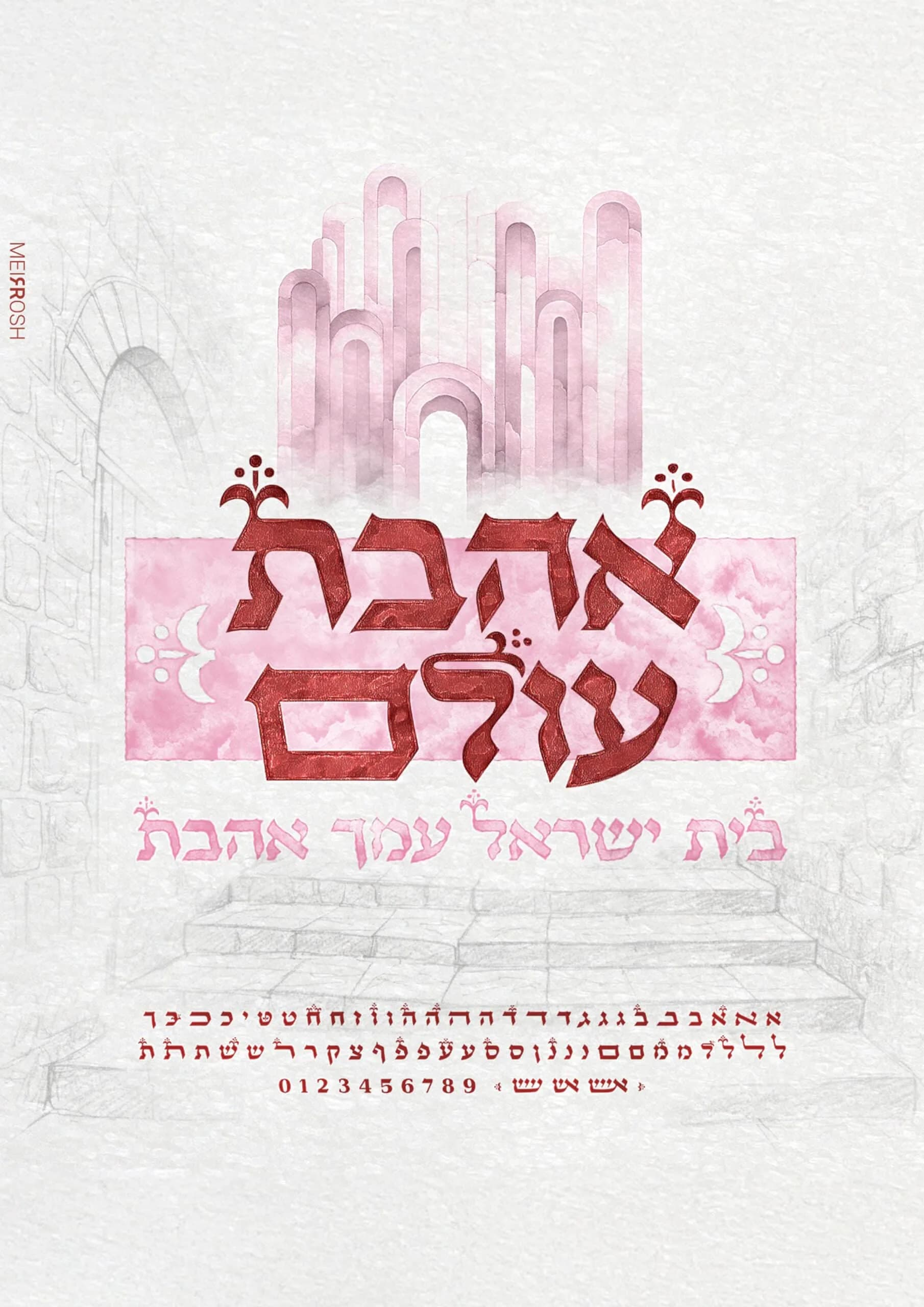
לפעמים, טיפוגרפיה היא הרבה יותר מסגנון של אותיות. היא נושאת בתוכה היסטוריה, תרבות, אמירה. פונט “שושן” נולד מתוך החיבור הזה – בין כתב עברי מסורתי לבין עיצוב מוקפד שמרגיש חגיגי, יוקרתי ונצחי. מתאים להזמנות לאירועים, כתובות, עיצובי קודש ומיתוג שמחפש עומק ויוקרה. נבנה באהבה לקליגרפיה יהודית ולמסורת של עיצוב אותיות מהודרות. משלב השראה היסטורית עם עיצוב עכשווי